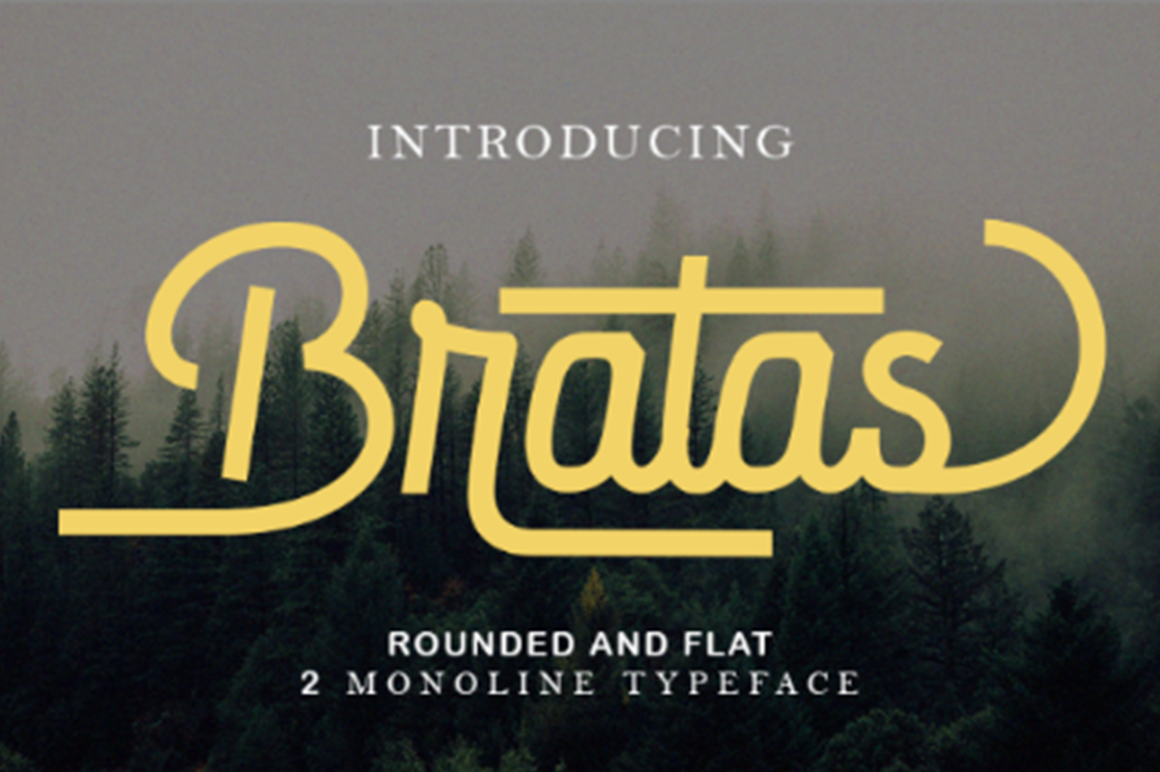
A ‘Bratas Font’ é uma seleção minimalista e elegante que se destaca entre as linhas de qualquer projeto editorial ou tipográfico. Inspirada no revival nostálgico dos anos 80, essa monoline typeface evoca a sofisticação da época com traços retos e diretos. Suas formas sóbrias remetem à arquitetura moderna de vidro e metal do passado recente, enquanto o toque moderno e vintage adiciona uma dose extra de originalidade para qualquer design. A Bratas Font é perfeita para designers que procuram uma fonte atemporal que seja tanto versátil quanto elegante, capaz de criar um arco-íris vibrante ou um texto sereno, dependendo do contexto em que se encaixar. Não importa o gosto pessoal ou a personalização que você deseje incorporar ao seu trabalho, essa fonte certamente atenderá suas expectativas, proporcionando uma experiência de design única e envolvente.